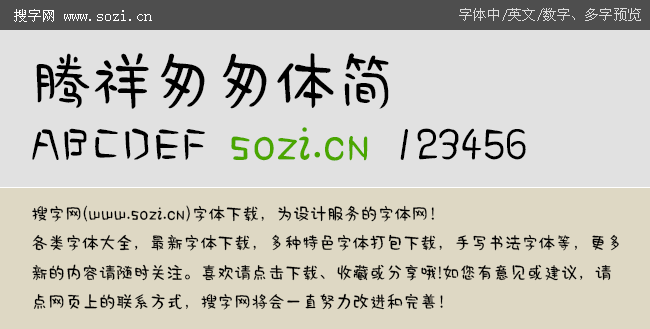
騰祥匆匆體簡(jiǎn)
搜字網(wǎng)提供一款騰祥匆匆體簡(jiǎn)中文藝術(shù)字體下載,騰祥匆匆體是一款全新的藝術(shù)字體,字跡活潑造型別致,給人極佳的視覺呈現(xiàn),可用于印刷出版、包裝設(shè)計(jì)、廣告設(shè)計(jì)、網(wǎng)頁(yè)設(shè)計(jì)等。